Font brush việt hóa có nét viết giống như nét cọ vẽ tay, tạo cảm giác tự nhiên, mang phong cách nghệ thuật cao. Font chữ nét cọ việt hóa được tìm kiếm nhiều để thiết kế logo, poster, bao bì sản phẩm hay quà tặng doanh nghiệp nên cần file chất lượng, không thiếu dấu tiếng Việt hay bản quyền phức tạp.
Tham khảo 15+ mẫu font chữ brush việt hóa đẹp
Font chữ brush việt hóa mang phong cách viết tay tự nhiên, được sử dụng trong thiết kế poster, logo, tiêu đề và các ấn phẩm sáng tạo. Dưới đây là 15+ mẫu font brush đẹp đã hỗ trợ tiếng Việt đầy đủ để bạn lựa chọn cho dự án thiết kế:
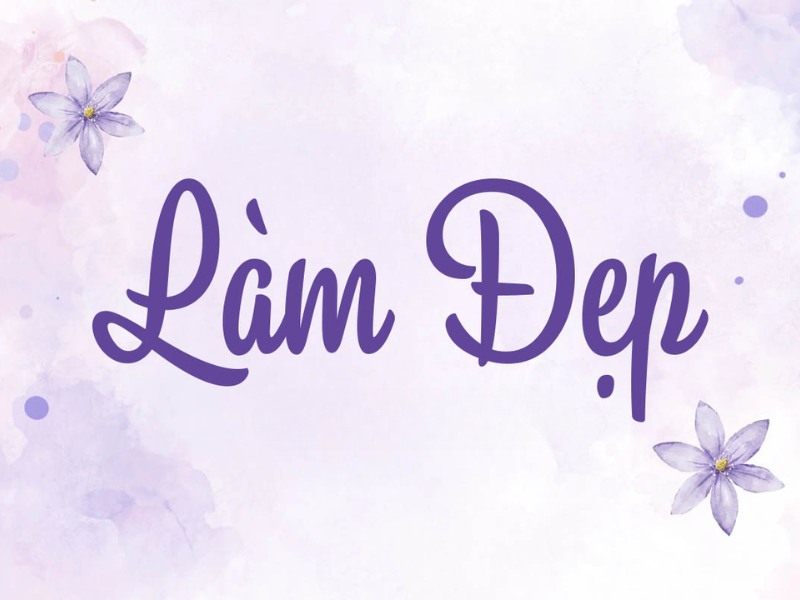
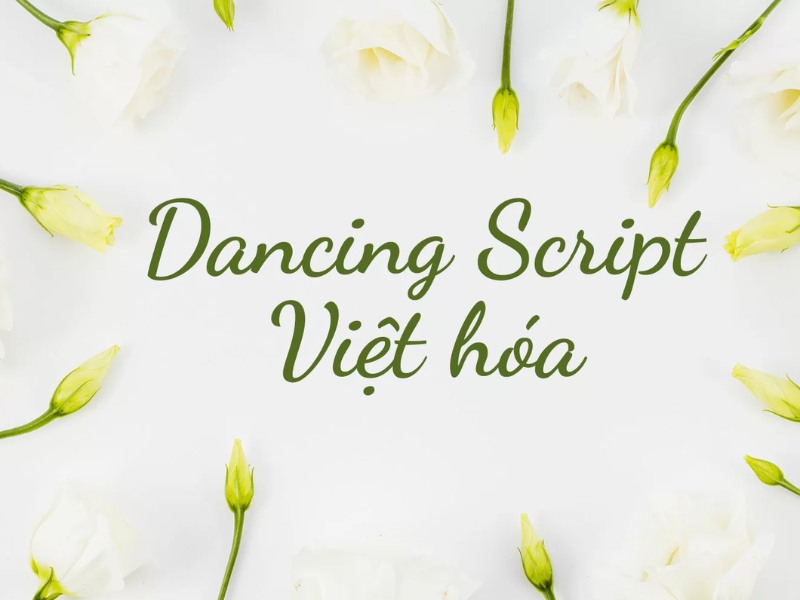
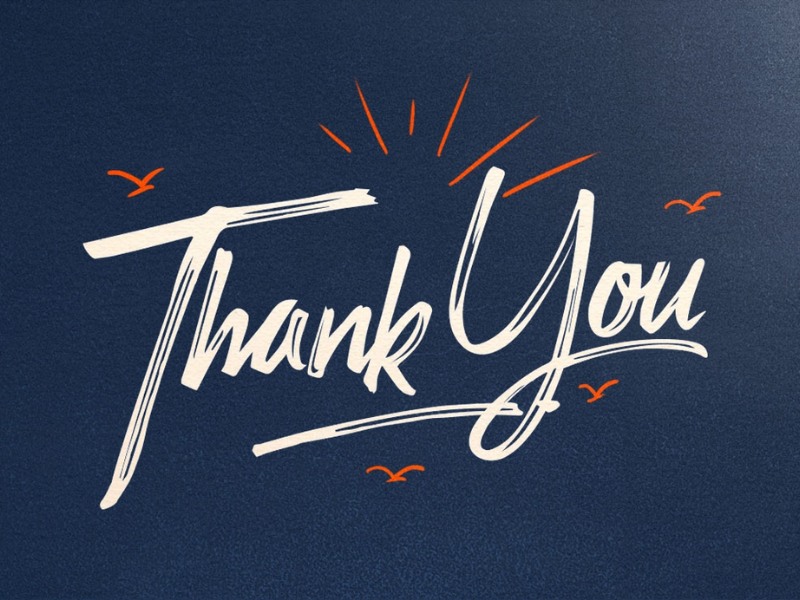
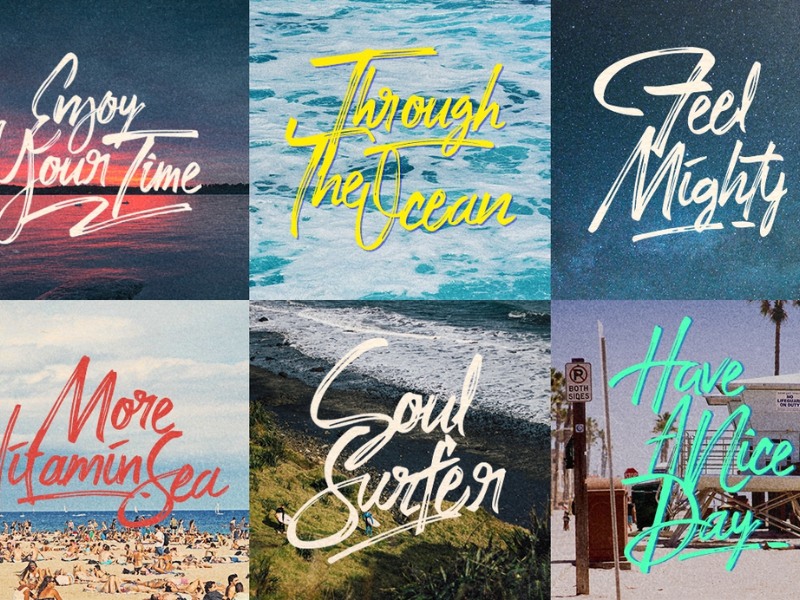
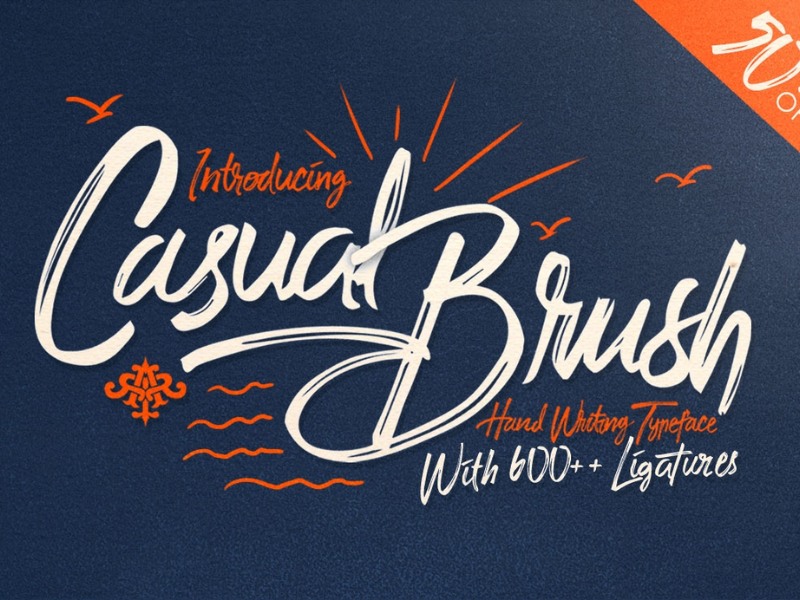
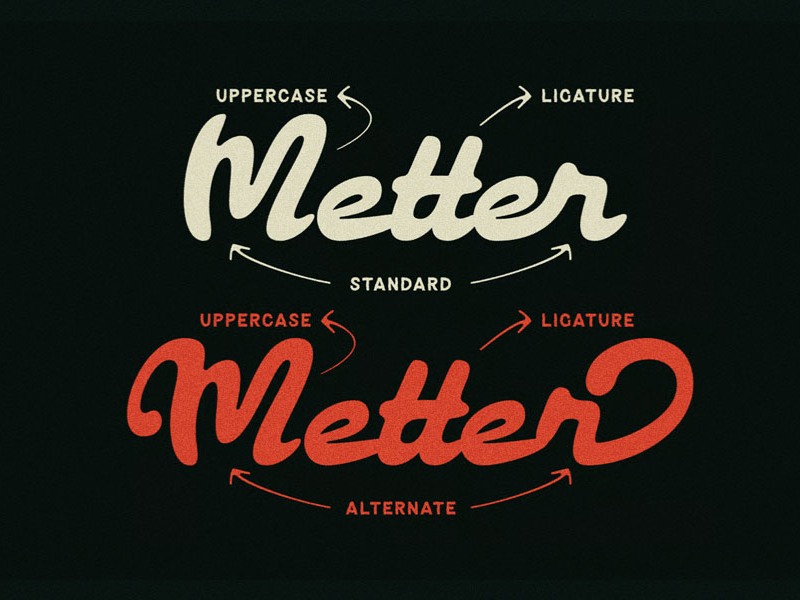
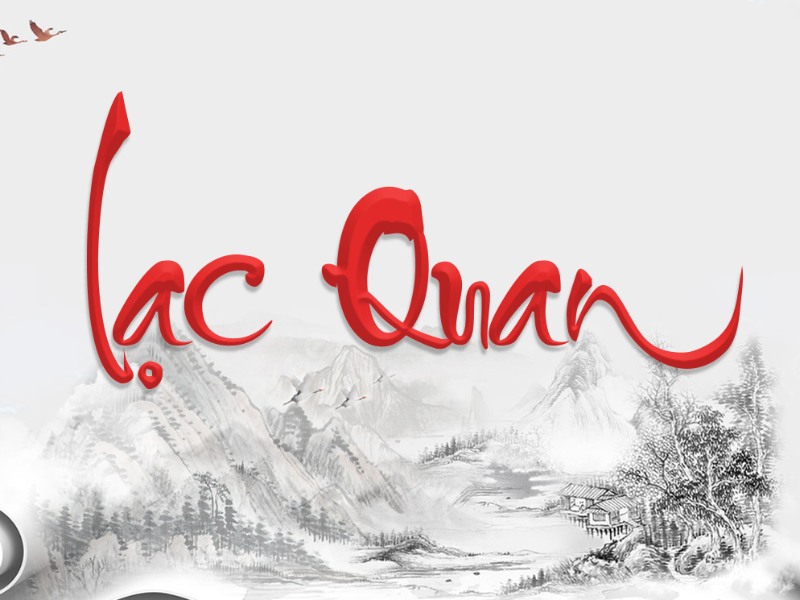
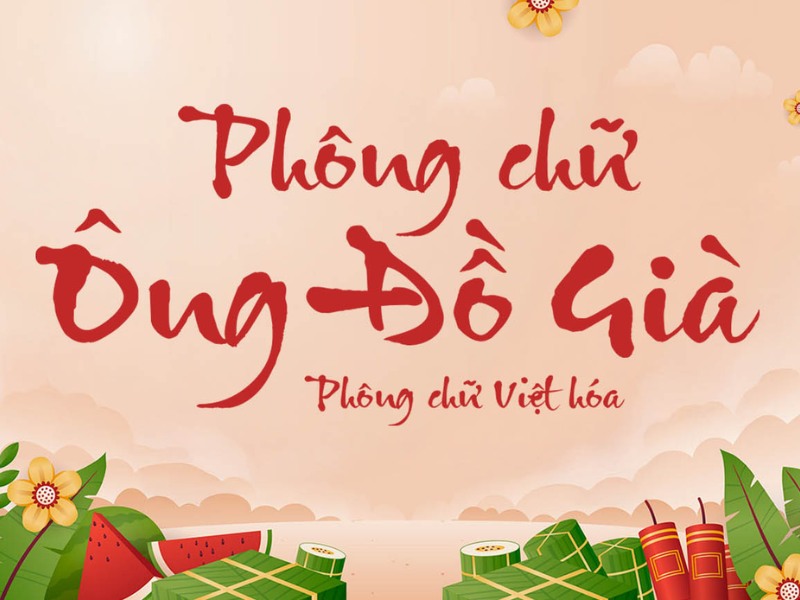
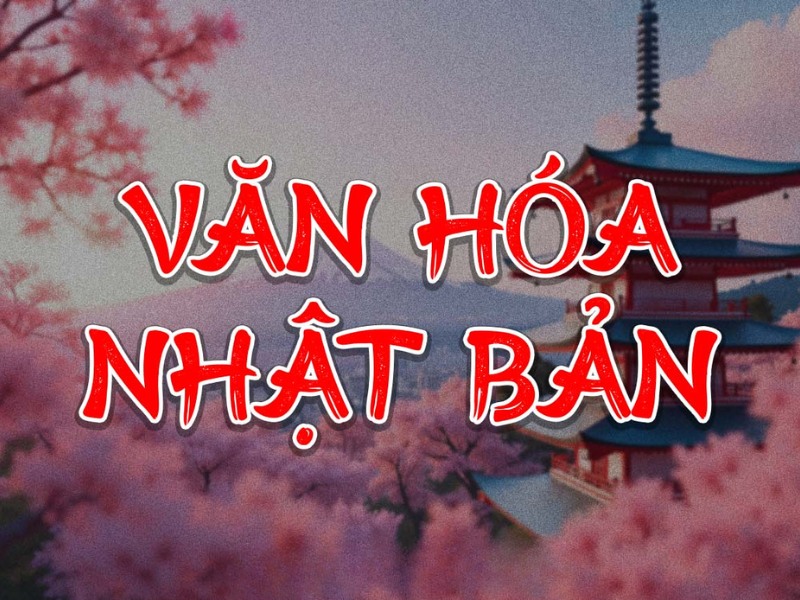
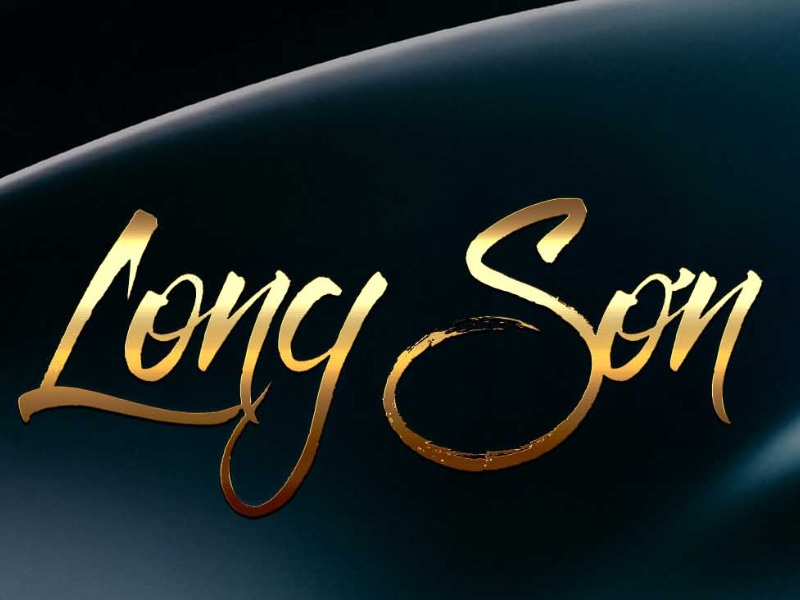
Bảng tổng hợp các font brush việt hóa được phân loại theo phong cách và ứng dụng để bạn dễ dàng lựa chọn phù hợp với thiết kế và in ấn của mình nhé:
Tên font |
Phong cách |
Ứng dụng |
SVN-Brush Script |
Nét mảnh, thanh thoát, hiện đại. | Logo thương hiệu thời trang, mỹ phẩm. |
UTM Brush VN |
Nét đậm, mạnh mẽ, có độ nghiêng. | Poster sự kiện, bao bì thực phẩm. |
VNI-Brush Hand |
Viết tay tự nhiên, nét đứt đoạn. | Thiệp cưới, thiệp mời, menu nhà hàng. |
Balinotion Brush |
Nét liền mạch, uyển chuyển | Túi giấy, hộp quà cao cấp. |
SVN-Casual Brush |
Năng động, trẻ trung, không cầu kỳ. | Áo thun, balo, quà tặng sinh viên. |
Các font brush việt hóa khác đáng chú ý: HVN-Brush Marker, Dancing Script VN, Pacifico VN, Yellowtail VN, Amatic SC VN, Kalam VN, Permanent Marker VN, Shadows Into Light VN, Caveat VN, Gloria Hallelujah VN.
Ý nghĩa và ứng dụng của font chữ nét cọ trong thiết kế
Font chữ nét cọ việt hóa thường được sử dụng khi thiết kế bao bì, quảng cáo và sản phẩm in ấn, mang những đặc điểm nổi bật như sau:
- Nét viết tự nhiên, không cứng nhắc: Font brush mô phỏng cách cầm cọ hoặc marker vẽ tay, tạo cảm giác gần gũi và thân thiện, phù hợp với các thương hiệu muốn truyền tải thông điệp ấm áp, con người.
- Hỗ trợ đầy đủ tiếng Việt: Các font chất lượng cao đều có bộ ký tự Unicode đầy đủ dấu thanh (á, à, ả, ã, ạ, ă, ắ, ằ…), không bị lỗi khi xuất bản hoặc in ấn. Bạn yên tâm sử dụng mà không lo bị thiếu dấu hay hiển thị sai.
- Đa dạng về độ dày nét: Có font nét mảnh (thin), regular, bold, extra bold để phù hợp với từng ứng dụng như tiêu đề lớn, slogan, hoặc chú thích nhỏ.
Font brush việt hóa xuất hiện rộng rãi trong nhiều sản phẩm thiết kế và in ấn như sau:
- Logo và nhận diện thương hiệu cho quán cafe, nhà hàng, cửa hàng handmade, spa làm đẹp.
- Bao bì sản phẩm thực phẩm như hộp đựng bánh kẹo, trà, cà phê, đồ uống.
- Quà tặng doanh nghiệp: hộp quà Tết, túi giấy kraft, áo thun đồng phục, bình giữ nhiệt, sổ tay.
- Thiệp mời, thiệp cưới, menu nhà hàng, backdrop sự kiện.
- Nội dung mạng xã hội: Instagram story, Facebook post, TikTok thumbnail.
04 sai lầm khi sử dụng font brush việt hóa
Việc sử dụng font chữ nét cọ cần tuân thủ một số nguyên tắc để đảm bảo chất lượng in ấn và tính thẩm mỹ:
- Dùng font không hỗ trợ đầy đủ tiếng Việt: Nhiều font brush miễn phí trên mạng chỉ hỗ trợ Latin cơ bản, khi gõ tiếng Việt sẽ bị lỗi dấu hoặc thiếu ký tự. Kết quả là bạn phải chỉnh sửa thủ công từng chữ trong Illustrator, tốn thời gian và dễ sai sót. Giải pháp là luôn test font với đầy đủ các dấu thanh trước khi bắt đầu thiết kế.
- Dùng font có bản quyền cho mục đích thương mại: Font brush đẹp có license cá nhân nên in logo lên quà tặng khách hàng mà không mua license thương mại sẽ dẫn đến tranh chấp bản quyền và phạt tiền. Bạn nên đọc kỹ điều khoản sử dụng hoặc mua license ($10-$50 tùy font) khi dùng cho mục đích kinh doanh.
- Lạm dụng font brush trong một thiết kế: Dùng quá nhiều font brush hoặc kết hợp nhiều kiểu brush khác nhau trong cùng một thiết kế làm mất cân bằng, rối mắt và khó đọc. Chỉ dùng tối đa 1 – 2 font brush cho heading/slogan, kết hợp với font sans-serif đơn giản (Arial, Roboto) cho phần body text.
- Dùng file PNG/JPG thay vì file vector: Tải ảnh mẫu font từ Google và dùng trực tiếp file PNG/JPG để in ấn khiến bị vỡ nét, logo mờ, răng cưa khi in trên khổ lớn như backdrop, bảng hiệu. Hãy cài đặt file font TTF/OTF gốc hoặc chuyển text thành outline vector trước khi gửi in.